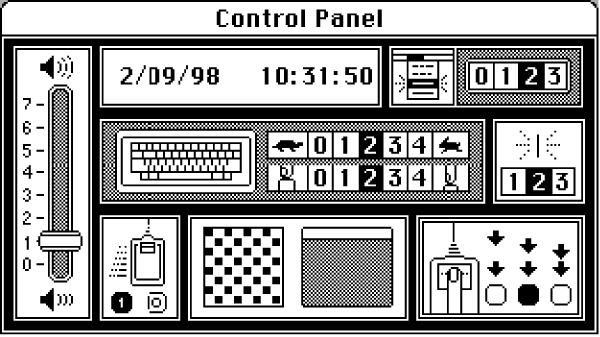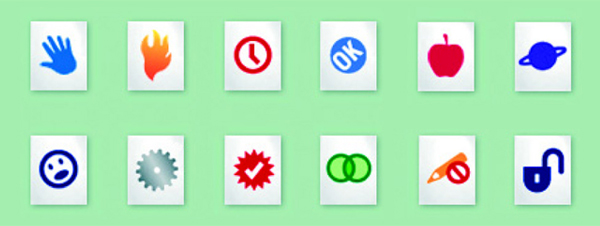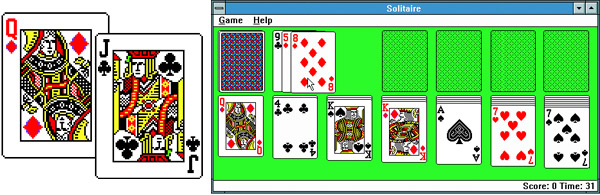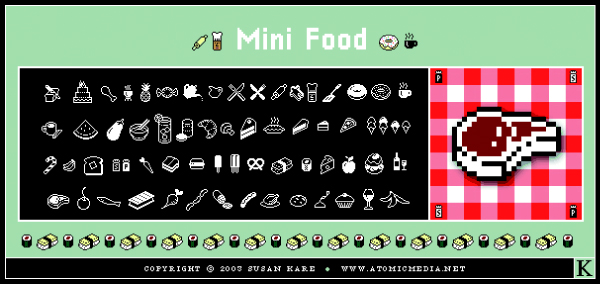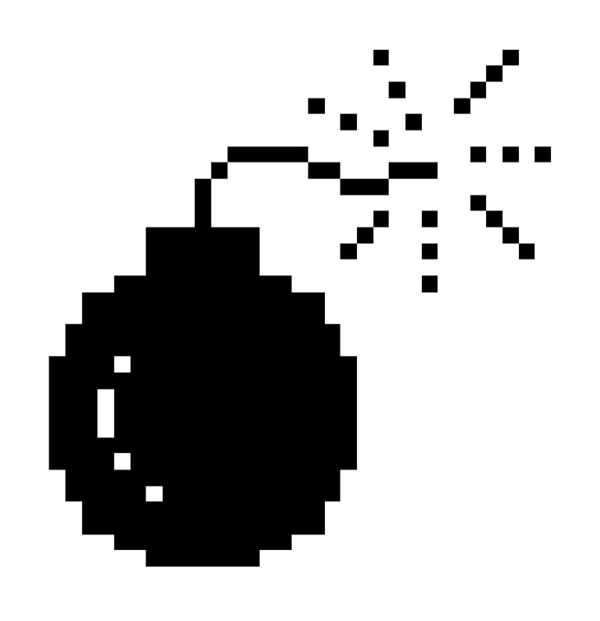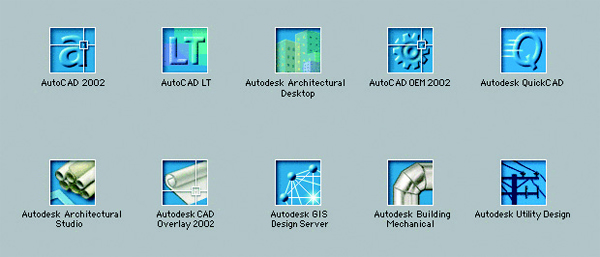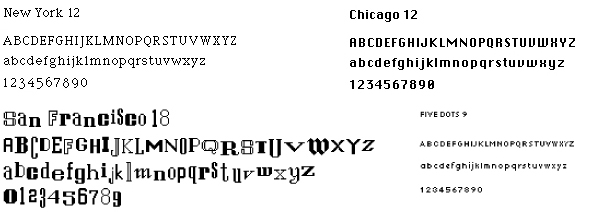
Susan Kare, el nacimiento del diseño gráfico para la interfaz digital
Los iconos y las tipografías de la estadounidense Susan Kare se han convertido en una parte fundamental de la industria del software. El diseñador gráfico mexicano Armin Vit entrevista para Experimenta a esta alumna aventajada de Paul Rand y Saul Steinberg que ha trabajado a lo largo de su carrera para clientes tan representativos del mundo de la informática como Apple o Microsoft.
Susan Kare.
En nuestro rol de diseñadores gráficos y comunicadores visuales, a menudo no sólo trabajamos con metáforas, sino que dependemos de ellas para crear mensajes que provoquen emociones, acciones y reacciones a la audiencia. Esto se consigue a través de imágenes y palabras. La yuxtaposición de fotografías o imágenes fuertes con textos de buena factura nos permite hacer carteles, cubiertas de libros, folletos o carátulas de discos.
Estos lienzos ofrecen una infinidad de posibilidades en las que la transmisión de una metáfora sólo está limitada por nuestra propia creatividad. En el cartel hay un tamaño y espacio que aprovechar; en la cubierta de un libro, una historia que contar; en el folleto, docenas de páginas para describir un producto o un servicio; en la cubierta de un disco, capas sobre las que construir una experiencia completa. Ahora imagine crear metáforas en un espacio tan reducido como la uña de un dedo y con un solo color, el negro – ah, y no lo olvide, las metáforas deben ser universalmente reconocibles.
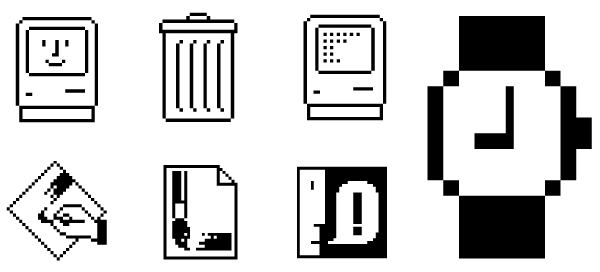
Selección de iconos para aplicaciones y sistemas Macintosh, Apple Computer, Susan Kare,1983-1984.
En casos extremos –pero no poco frecuentes– éstas son las limitaciones y condiciones bajo las que trabaja Susan Kare. En su papel de diseñadora de iconos e interfaces con el usuario, ha aprovechado el poder de la metáfora para crear interfaces sencillos, humanos e intuitivos para sistemas operativos de ordenadores, teléfonos móviles, dispositivos de mano, sitios web… hasta para relojes.
Un recorrido por las colecciones de iconos de Kare muestra sirenas que flotan, conejos que saltan, zanahorias que penden y papeleras que engordan. Tal vez el ejemplo más emblemático sea el temido icono de una bomba que forma parte del sistema operativo original de Macintosh: el ordenador no va a explotar, de eso podemos estar seguros, no con una bomba tan curiosa como ésta, pero la sensación de peligro inminente para el sistema se transmite de forma clara y sencilla. No obstante, en este intento de crear «espacios» óptimos, no todo son metáforas.
La simplificación, organización y síntesis de elementos son cualidades que siempre entran en juego – en proyectos en los que la claridad, simplicidad y utilidad son los objetivos principales. «Todavía creo», dice Kare con orgullo, haciendo referencia a Alan Kay, un pionero en el mundo de los ordenadores personales, «en el viejo refrán que dice que ‘las cosas sencillas deben ser sencillas, mientras que las cosas complicadas deben ser posibles’».
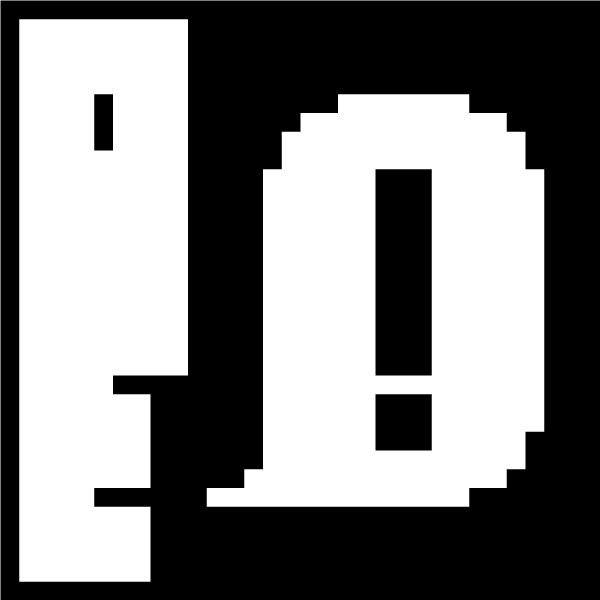
Lo sencillo no es tan sencillo como parece
La sencillez es un tema recurrente en el corpus de su obra, incluso en proyectos que son todo menos sencillos. Tómese, por ejemplo, su primer encargo en 1983: el diseño de fuentes, iconos y look and feel para Macintosh. Por vez primera. Con un master y un doctorado en Bellas Artes de la Universidad de Nueva York, un fuerte interés en la escultura y un puesto de conservadora adjunta en el Museo de Bellas Artes de San Francisco, crear gráficos para ordenadores no parecía una transición profesional lógica.
«Los gráficos Bitmap son como los mosaicos, los bordados sobre cañamazo u otras expresiones artísticas pseudodigitales», Kare explicó en una ocasión, «las cuales ya había practicado antes de ir a Apple» (1) Andy Hertzfeld, uno de los principales programadores y creadores del primer ordenador Apple, y un buen amigo de Kare, la contrató para realizar esta labor.
Cairo, tipografía dingbats diseñada en mapa de bits para el primer Macintosh, Susan Kare.
Trabajando sobre una cuadrícula con un editor de iconos rudimentario, Kare, en colaboración con el equipo, desarrolló el primer conjunto de iconos del sistema. Entre ellos se encontraba la imagen del Happy Mac que aparecía en la pantalla inicial, la papelera, el reloj, la bomba y el archivo, iconos de aplicaciones y de archivos. Las primeras fuentes Mac como Chicago (reestablecida en el interfaz iPod de Apple), New York y Geneva también fueron desarrolladas por Kare en esta etapa.
New York, Chicago, San Francisco, Five Dots fuentes bitmap diseñadas para el primer Macintosh, Susan Kare.
El recuerdo de las experiencias de Kare durante el desarrollo de esa monumental tarea nos da una idea clara de su metodología. Lo que destaca es su persistencia en no dejar que el medio limite la capacidad de su trabajo, buscando las formas de fortalecerlo. El primer ordenador Apple sólo disponía de píxeles negros –el color no era una opción en ese momento– de forma que tuvo que hacer uso de una enorme creatividad para sacar el máximo partido de la tecnología disponible, que consistía en una «cuadrícula con espacios que cambiaban de blanco a negro» (2).
(2). Ibid.
(3). Dithering es una técnica utilizada en la creación de gráficos de ordenador para dar la impresión de varios tonos de gris o colores adicionales mediante la distribución de los píxeles de la pantalla o los puntos imagesetter de una imagen.